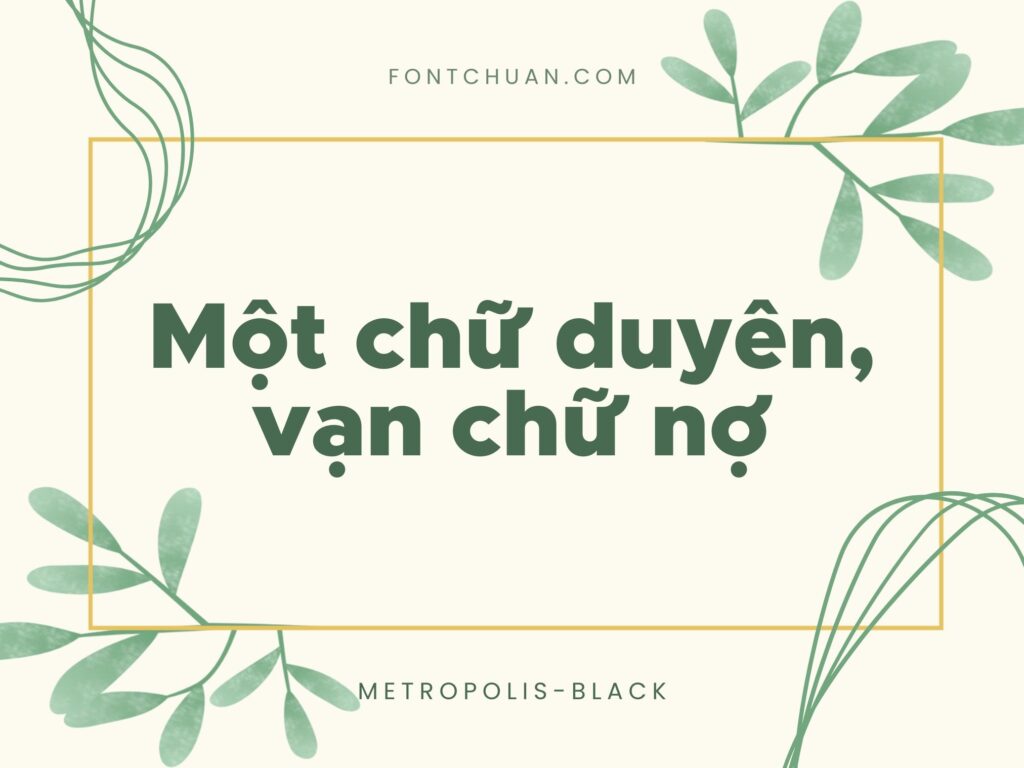
Font Metropolis+ Việt Hóa
Tác giả Font: Chris Simpson
Việt hóa bởi: Catterio
Metropolis là một font sans-serif hiện đại và hình học, được thiết kế bởi Chris Simpson. Lấy cảm hứng từ các kiểu chữ geometric và minimalist sans-serif phổ biến của thiên niên kỷ mới, Metropolis mang đến sự cân bằng giữa tính thẩm mỹ và khả năng đọc. Bộ font bao gồm 18 kiểu chữ với 9 trọng lượng từ Thin đến Black, cùng các phiên bản nghiêng tương ứng. Metropolis hỗ trợ tiếng Việt và nhiều ngôn ngữ khác, được sưu tầm và đăng bởi thành viên của Font Chuẩn.
Nhờ thiết kế gọn gàng, sắc nét và chuyên nghiệp, Metropolis không chỉ là một lựa chọn lý tưởng cho các dự án thương hiệu hay nội dung số, mà còn được đánh giá cao như một Font chữ bất động sản tiêu biểu. Với khả năng thể hiện sự sang trọng, hiện đại và đáng tin cậy, font này rất phù hợp để ứng dụng trong các ấn phẩm quảng bá dự án, bảng hiệu công ty hoặc website giới thiệu bất động sản.